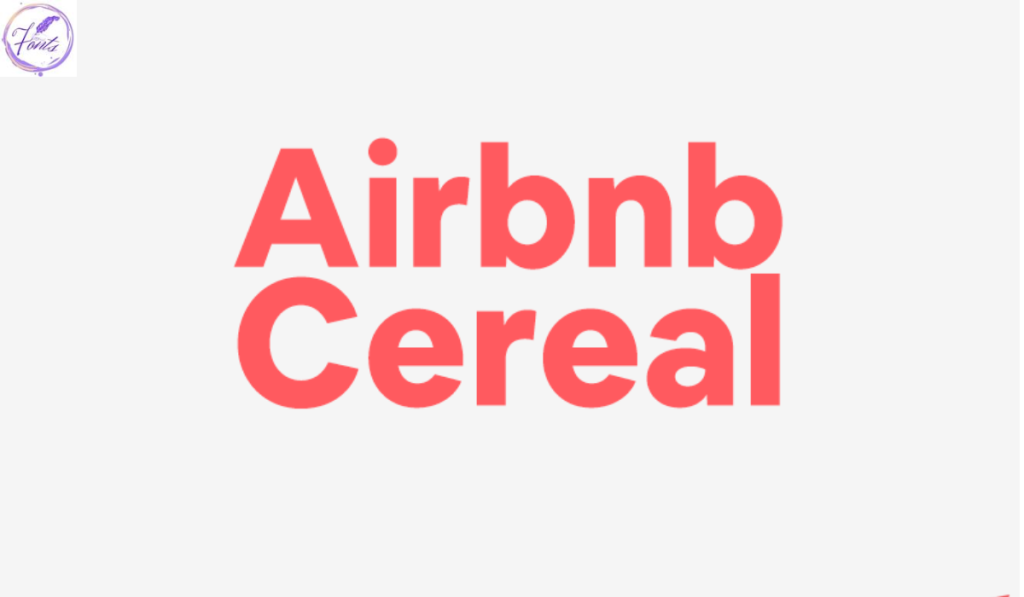
Tác giả: Dalton Maag
Bộ Font: Cereal
Phân loại: Cá tính, Độc đáo, Thân thiện, Hiện đại
Kiểu chữ: Kiểu chữ không chân (sans-serif)
Độ dày: Light, Book, Medium, Bold, Extra Bold, Black
Airbnb Cereal font là phông chữ sans-serif hiện đại, được thiết kế bởi Dalton Maag và ra mắt lần đầu vào năm 2018. Font này được phát triển độc quyền cho Airbnb, với mục tiêu tạo ra sự thân thiện và dễ đọc trong mọi ứng dụng, từ giao diện người dùng trên web đến các tài liệu in ấn. Phiên bản việt hóa của Airbnb Cereal hỗ trợ đầy đủ các ký tự tiếng Việt, giúp người dùng tại Việt Nam có thể dễ dàng áp dụng trong các dự án thiết kế đa dạng.
Đánh giá airbnb cereal font
Airbnb Cereal font được đánh giá cao bởi cộng đồng thiết kế nhờ vào tính thẩm mỹ cao và khả năng ứng dụng linh hoạt. Phông chữ này nổi bật với các đường nét mềm mại, dễ đọc và phù hợp với nhiều kích thước hiển thị khác nhau. Các nhà thiết kế đặc biệt yêu thích sự hiện đại và tinh tế của Airbnb Cereal, làm cho nó trở thành lựa chọn lý tưởng cho các dự án từ thiết kế giao diện người dùng, quảng cáo đến in ấn. Với phiên bản việt hóa, font này càng trở nên hữu dụng hơn trong các dự án tại Việt Nam.